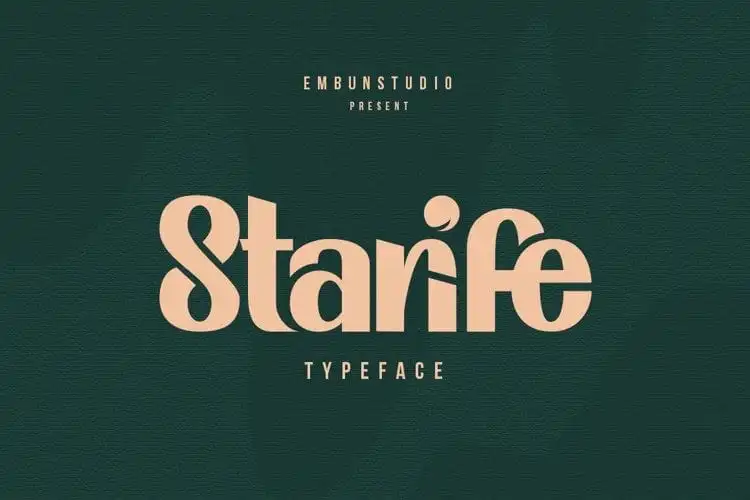
Starife Display Font – Fonte Grátis
Starife Display Font
A Starife Display Font é uma sans serif que traz elegância e sofisticação ao seu design. Seu estilo luxuoso, limpo e chic contrasta perfeitamente com os elementos de visualidade e elegância que ela oferece. Possui alternativas e ligaturas para garantir um texto fluido e profissional. O suporte multilíngue completa sua funcionalidade perfeita para projetos editoriais, criação de logos, branding de roupas, embalagens de produtos, cabeçalhos de revistas ou simplesmente como uma overlay de texto elegante para qualquer imagem de fundo. Esta fonte é uma escolha inteligente para quem busca um toque sofisticado e moderno em seus projetos visuais.